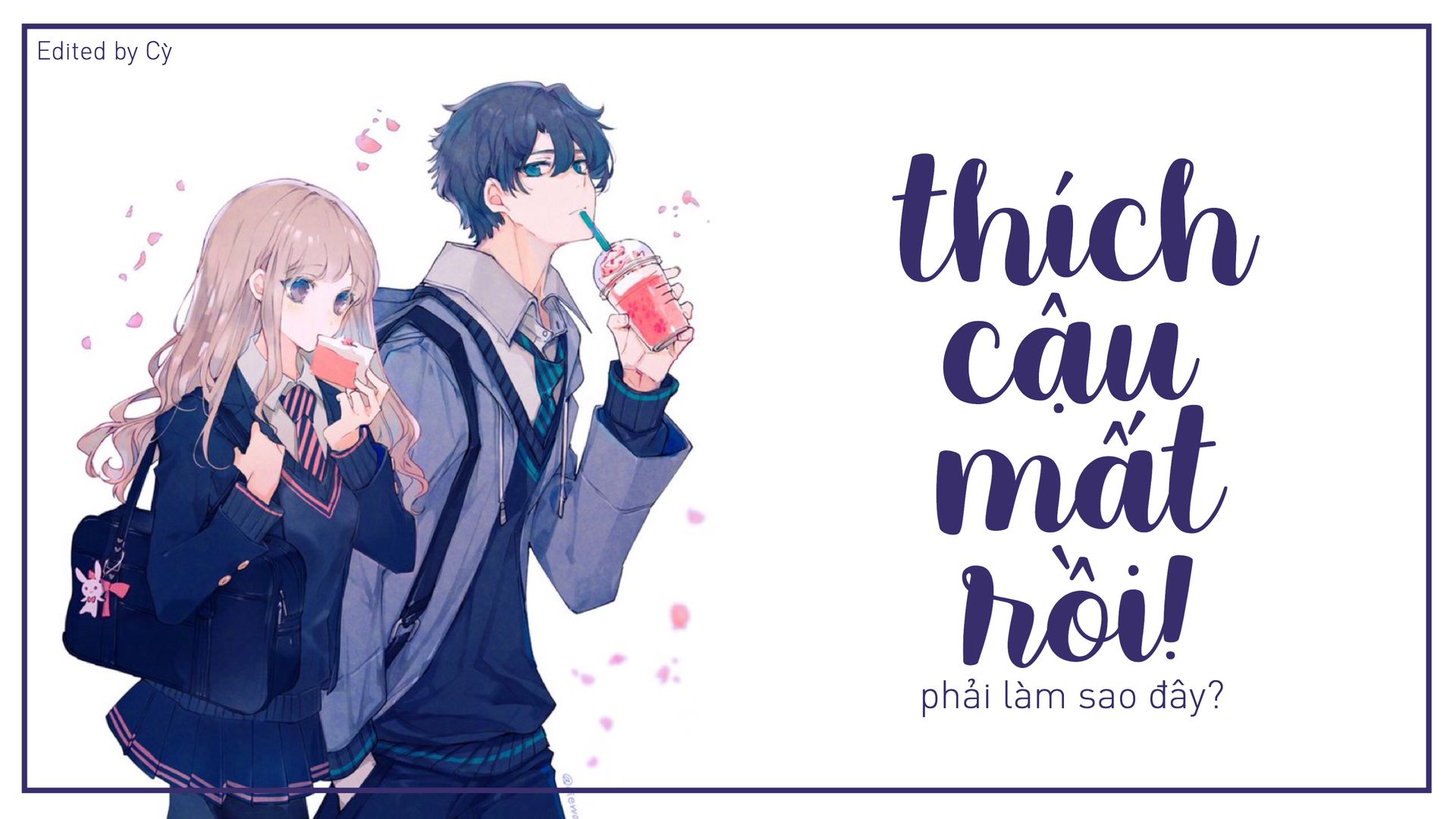
[font] moonbright
anyway, đây là font cỳ mới việt hoá bằng app đấy
cỳ đúng thích font này luôn ớ, nhìn xinh gì đâu ><
tên font: moonbright regular
tác giả: brittney murphy